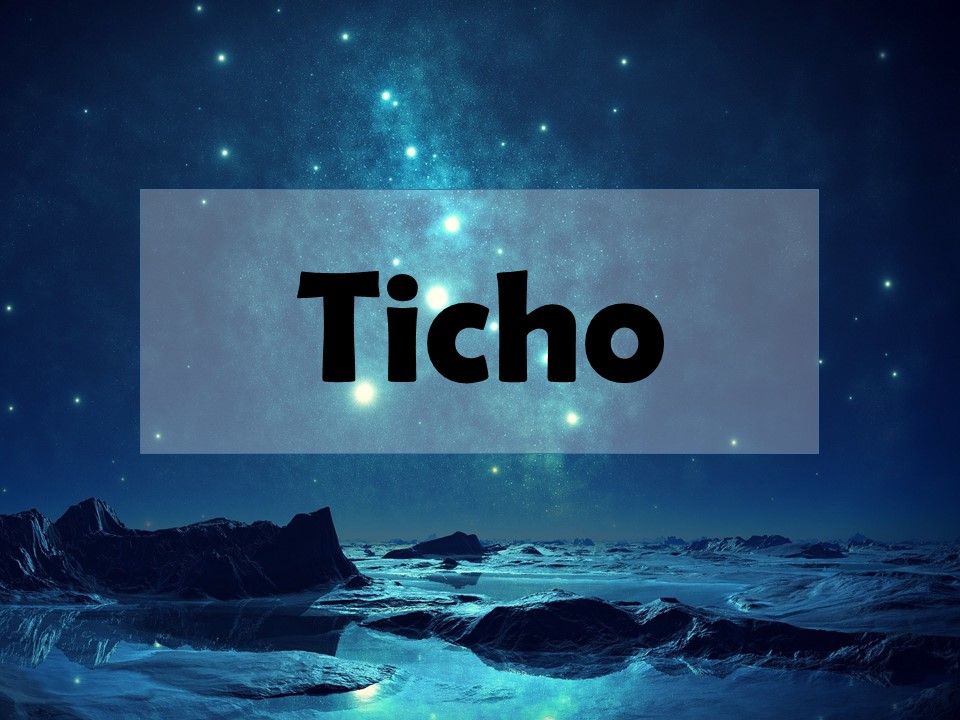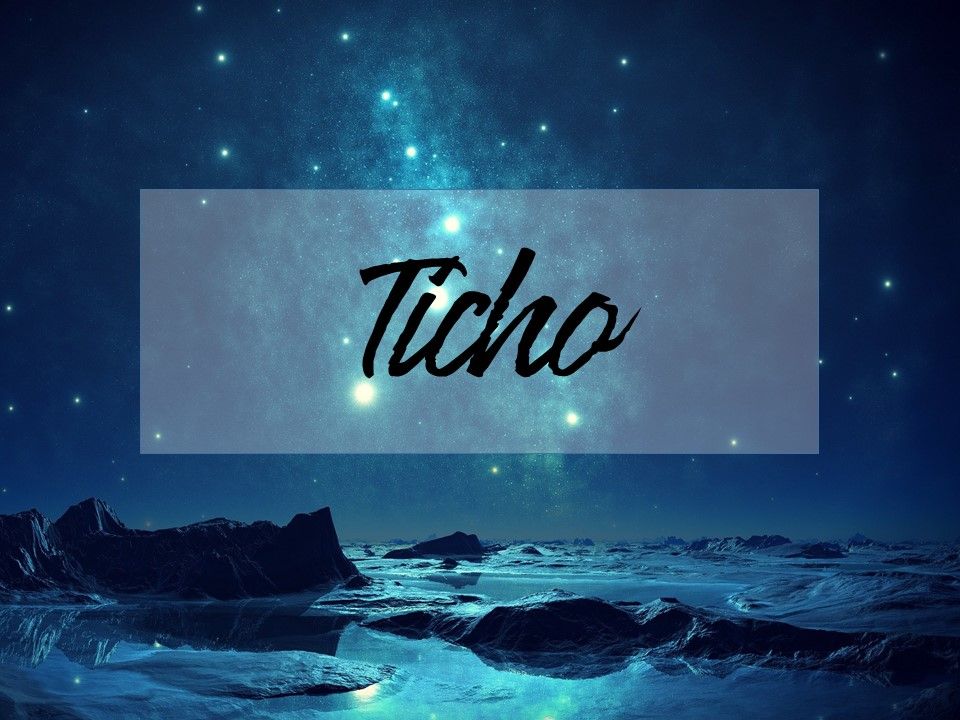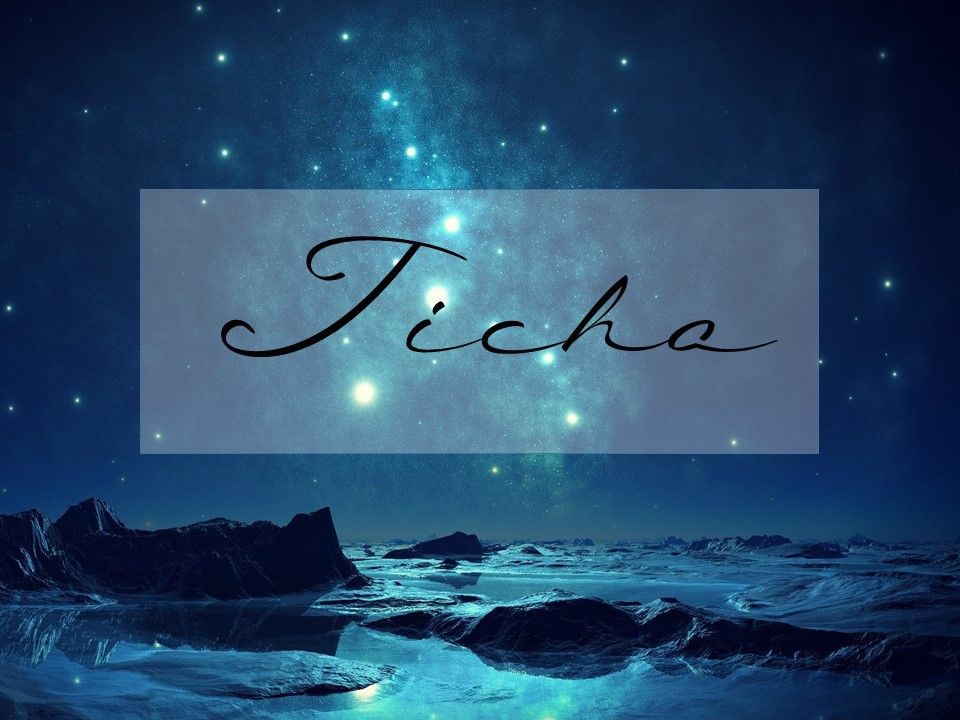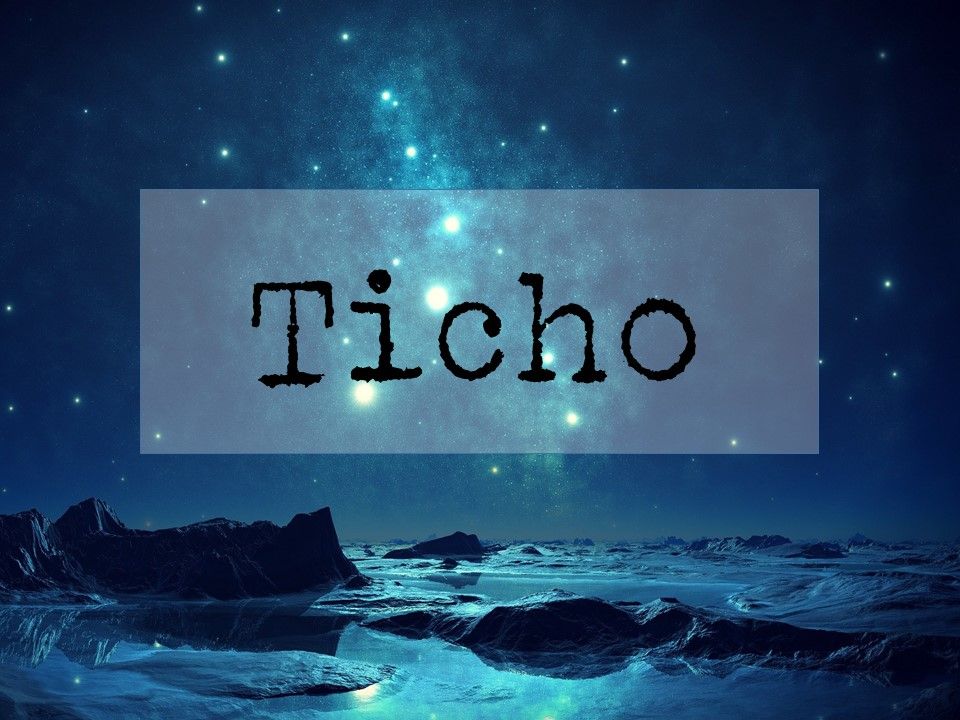
„Nad shrbenými zády v obnošeném svetru záplatovaném na lokti, se vznášel oblak dýmu z cigarety, která trčela ze skleněného popelníku. Sloužil jako těžítko na listech papíru, které vypadávaly, hustě popsané, z psacího stroje. Dým, obnošený svetr i popelník byly svědky zrození každého nového románu Petera Larrsona.“
Příběhy nás dokáží vtáhnout do děje, přenést do jiného světa. Miluju knihy, když se začtu, dokážu na hodiny vytěsnit vše okolo. Pokaždé si z knihovny odnáším stoh knih, ale toto kouzlo vtáhnutí do jiné dimenze, dokáže jenom střípek z nich. Ostatní po jedné kapitole zavírám a vracím zpět do knihovny.
Čím to je?
Nemůžu mluvit za ostatní, určitě to máme každý jinak, ale já potřebuji víc, než jenom sledovat linku příběhu jako honící pes s nosem u země, rozmotávat propletence lidských dialogů, vztahů i (ne)vztahů a těšit se jako to dopadne.
Kniha, která mne dokáže vtáhnout, vlastně vůbec nemusí mít nějaký výjimečný děj. To, co přenáší do jiného světa, je schopnost vzbudit lavinu představ, emocí, asociací.
Kdybych na začátku napsala:
„Peter Larrson ťukal na psacím stroji další knihu a u toho kouřil“
dozvěděli byste se to samé. Ale cítili byste to samé? (Nepodsouvám vám, že se máte cítit lépe při první ukázce, ale zaručeně ve vás každý text budí rozdílné emoce).
To samé platí u filmů. Miluju klasickou francouzskou kinematografii, ve které není téměř žádná akce.
Hudba, která podkreslí procházku na pláži, klapot podpatků servírky v kavárničce na Place Pigalle (protože ve francouzských filmech nosí servírky střevíce, ne zdravotní obuv), šumění deště za okny taxíku, kde sedí (mlčky) hrdina…
Málo se v nich mluví, ale o to víc v nich prožíváte. V hlavní roli jsou naše emoce, asociace, představy, ztotožňujeme se o to víc, že nemusíme řešit slova a jejich význam.
Viděli jste film Muž a žena? Banálnější téma byste těžko hledali, dialogy jsou improvizované – chybí jim hodně do vytříbenosti, přesto patří k nesmrtelným filmům. A jsem si jistá, že hudbu z filmu zná téměř každý z nás (starší 35 let).
„Jen málo dialogů, zato plno nádherných záběrů v barvě i v černobílém. Spolu s hudbou působí spíše na city než na mozek, jinak řečeno, tenhle příběh se musí spíš prožívat, než aby se o něm přemýšlelo.“
recenze od Flanker.27
A proč toto vše píšu na blog o psychologii fontů?
Písmo má stejnou moc jako hudba a obraz.
Podíváte se na něj a už se nějak cítíte. Vnímáte tvary, linky, prázdná místa, křivky, hrany… a okamžitě nastupují emoce. Vnímáte je stejně, jako intonaci hlasu, jako řeč barev, jako hudbu v pozadí. Jak bych vám to zprostředkovala…
Nedávno jsem četla knihu od Aleny Mornštajnové, Tiché roky. Víte, jak paní Mornštajnová píše – nechcete, aby kniha skončila. A jedna věta z této knihy mi v hlavě rezonovala celý den.
„Existují různé druhy ticha.“
Alena Mornštajnová
Jak pravdivé.
Kdybych měla spočítat, kolik druhů ticha rozeznávám, bylo by jich minimálně 6.
Kdybych měla popsat, jak se v nich cítím, jak je prožívám, nejlépe mi v tom pomohou právě fonty. Předám jimi daleko víc, než jenom slovy.
Zkuste si to také! Jaké ticho vnímáte teď:
a teď:
Jak se cítíte, když je kolem vás takovéto ticho:
A co vám přinese takové:
Každé písmo vás povede jinam, kdyby ho použili jako titulek filmu, tak u něj slyšíte jinou hudbu. Každé z nich představuje jiný žánr a má jiné hrdiny.
Když se podíváte na každé písmo zvlášť a hodně si ho zvětšíte, naladí vás na váš vlastní příběh:
1/ Ticho útulné
Ticho, které je tak měkké, všeobjímající, provoněné bezpečím a známou vůní, do kterého se můžeme zabalit jako do deky. Může to být ticho těšící se na příchod někoho blízkého, naplněné láskou až k prasknutí a chutí obejmout ho a nepustit. Je to ticho, které můžete vnímat, když se dospělosti zavřete na návštěvě u rodičů do svého dětského pokoje. Zavalí vás vzpomínky (ty hezké), známé vůně a nechá vás prožít vlnu emocí.
2/ Ticho mrtvé
Stojíte, sedíte, ležíte a nechcete nic slyšet. Schovka před bezradností, emocemi, druhými. Nechte mne být. Solné jezero, ve kterém uhynul život, mrtvá měsíční krajina. Potřebujete chvíli neslyšet, nevnímat, necítit, jenom existovat. Víte, že až bude potřeba, přiletí Fénix, v poušti vykvete růže Malého prince a do ticha proniknou zvuky, které vás dokáží z něj vytrhnout. I přes jeho pasivitu a nečinnost může být jediným lékem na život. Ticho, které vám pomůže ho poskládat tak, jak chcete.
3/ Ticho tíživé, napjaté
Ticho před bouří, kdy lidé i zvířata hledají úkryt. Ticho před hádkou, kdy je ve vzduchu úplně stejné bouřkové napětí a my máme chuť se někde schovat, uniknout bleskům a hromobití slov. Ticho nervózní a křehké, které je naplněné nevyřčenými slovy a hádkou, která visí ve vzduchu. Ticho, které se nedá vydržet.
4/ Ticho cesty k duši
Volající ke spánku, kdy čas pozbývá na významu, chvíle vědomí se zkracují a pomalu rozplývají v říši Morfea.
Tvary ztrácí na určitosti, mysl ztrácí na racionalitě a právě v této chvíli roztahuje křídla intuice a duše. Není času, není omezení, není limitů. A za chvíli není ani vědomí, rozplynulo se a čeká na ráno. Stejné ticho můžeme prožívat při meditaci, tai-chi, malování, kdy stejným způsobem máme rande s duší.
Umožní vám při čtení jakéhokoli textu cítit něco, co hned nedokážete popsat slovy. Ani to nevnímáte. Ani nad tím nepřemýšlíte.
Emoce. Pocity.
Pomůže vám předat druhým atmosféru, náladu, asociace i kontext.
Font je přímo zodpovědný za to, jak se při čtení textu budete cítit.
A toho můžete skvěle využít. Ne, dneska nebudu psát o tom, jak může zapůsobit na vaše čtenáře, na cílovou skupinu v pojetí marketingu. Zkusme dneska vnímat písmo jako zdroj inspirace. Naší vlastní inspirace.